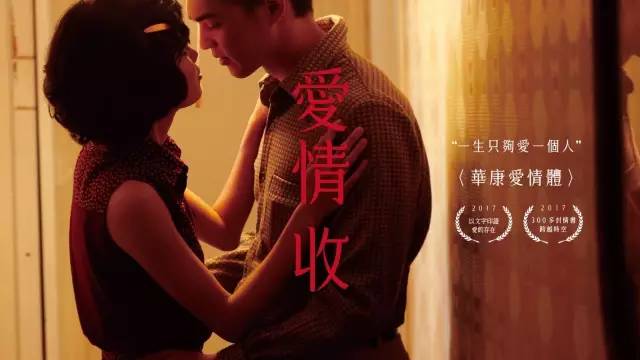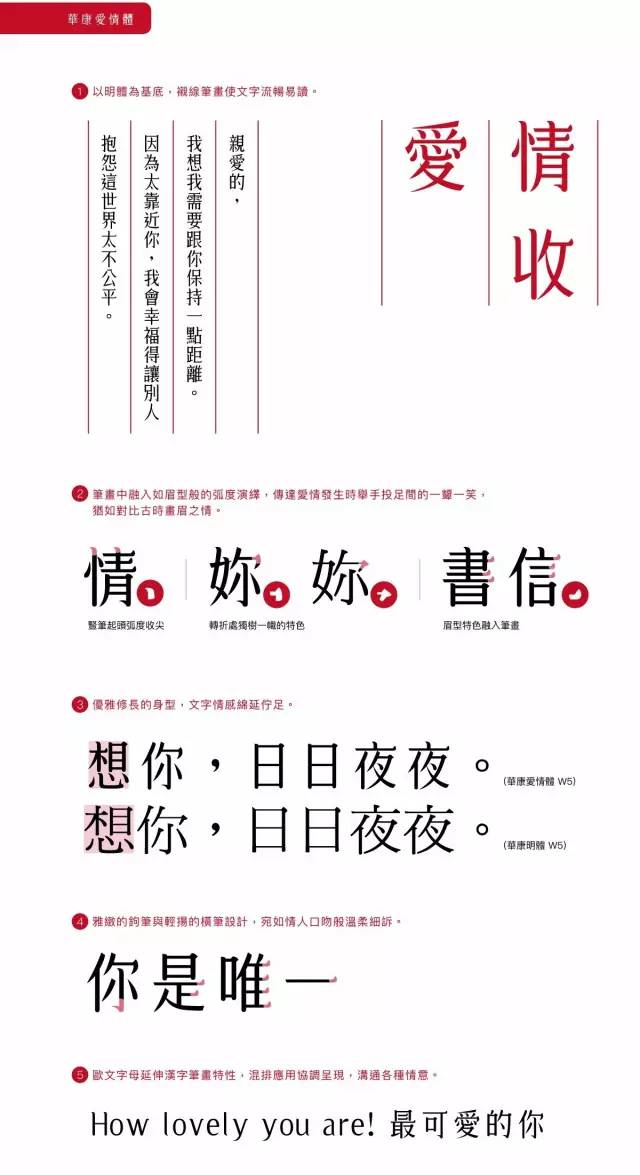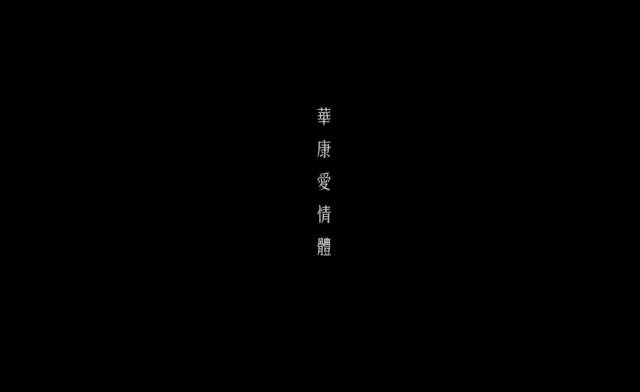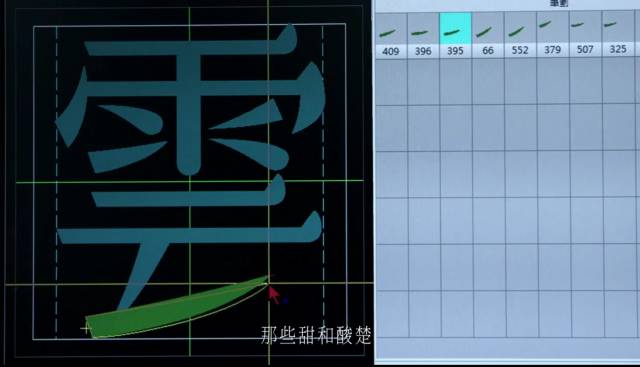
华康爱情体,这字体是跨越半世纪的爱情故事
我们有幸与一则半世纪前深刻的爱情相遇,故事的男主角国辉透过手写情书,以文字勾勒他和女主角云爱情的形状,以文字许诺他俩间爱情的重量,三百多封的〈邱月云小姐收〉,经纬交织成炽烈真挚的故事,字字印证了爱情的存在,也印证了他们的存在。然而这份爱情不只属于他们,我们更探寻那一笔一画之所以成为爱情载体的原因,将文字的情意汲取而出,凝聚出足以表述爱情的字型,华康爱情体。
关于《爱情收》
-起-
故事的主角钟国辉,在户政事务所负责誊写各式各样的户籍资料,每日亲笔书写人们的出生、死亡、结婚、迁徙,犹如爱的诞生、逝去、结合、分离。
十九岁那年,他认识了杂货店老板的十七岁女儿,邱月云。此后他振笔疾书的不再只有别人的人生,还有三百多封趁工作时偷偷写给邱月云的情书,每一个字迹都装载着爱。钢笔写下的每个字迹,拆开来看,和那些冰冷的生死文件并无不同;但在赤红的十行信纸中串联,却是浓密炽烈情感的倾泻。
「亲爱的云,我有说不尽的情意,……」薄薄一张信纸能承重多少?他未曾想过。他只知道每每拿起笔来,就想倾尽心中所有的爱,仿佛信一送出,吻就能到达对方颊上。
-承-
国辉修长翩然的字,悉心刻划与月云的爱情,时而激情、时而日常。
「附带寄给妳一个吻吧,吻在妳身体允许我吻的地方,反正随便妳的安排吧!」
「前几天妈买了许多小鸭子来饲养着,妈说是养着等妳回来端节为妳加菜之用,到时我也可托妳的福而大打牙祭呢!」
一九六五年,他们结婚。两人的身份证写上彼此姓名,户口名簿添了新生儿,随着手写的「迁入」两字展开新生活。这些笔画都扎扎实实地写进他们的旅程中,对两人而言,白头到老不仅是美好想像,更是个必然的人生里程。
-转-
三十年后的一个下午,钟国辉意外身亡。两人将至的未来,在远方戛然而止。此后,邱月云独自渡过无人知晓的七千六百多个日子,直到二○一五年离世。次女钟慧君整理邱月云遗物时,意外从衣柜深处取出一个陈旧斑驳的铁盒。
打开一看,竟是父亲写给母亲的三百多封情书;父亲字迹如新,信封也仿佛才刚被母亲急急地拆开而已。
看到这三百多封情书被如此妥善地保存,至此已不忍想像,过去二十一年,邱月云是如何熬过辗转难眠的孤独长夜,又是第几次深夜起身,念起当时的一切如常,于是再次开信,反覆读到信纸渐薄透光。
-合-
这些文字如钟国辉仍在左右一般,陪伴了邱月云长达二十一年,字字印证了爱情的存在,也印证了他们的存在。然而,这份爱情不只属于他们,更属于你我。
因为文字,我们存在、华康字型存在,我们探寻这三百多封书信中的情意,与古今之爱情作对比,探索那一笔一画之所以成为爱情载体的原因,最终凝聚出足以表述爱情的形状。将国辉每一封情书中手写的温度与情意,淬链、凝聚,让其修长翩然的字迹比之于优雅的字型结构;炽烈真挚的爱意,则以具象的雅致勾笔、与轻扬的横笔设计揣度,宛如情人口吻般温柔细诉。华康爱情体,属于你我爱情的字型。
爱情的模样
爱情萌芽之际,许多情感的流动来自眉目传情。华康近距离探寻《爱情收》主人翁书写爱情时的喜怒哀乐,从字里行间看见爱情充满生命力的流动,将文字的情意汲取而出,对照古时男女间的画眉情怀,发觉爱情的晶莹之处便是凝聚在这眉梢的一颦一笑。深刻探究后更确信,渴望质朴而炽烈的爱情,是始终存在的人性;无关时间的流动,古今相同。如此细细比对思忖,第一套属于爱情的字型便酝酿而生。
因此在台湾,我们赋予此字型爱情之名,正式称为《华康爱情体》。
DynaFont爱情体的字型特色
华康爱情体以明体为基底,衬线笔画使文字流畅易读;雅致的钩笔与轻扬的横笔设计,之于字体有如眉毛之于眼神,点缀喜怒,为字字注入饱满情绪,更能表现文意的抑扬顿挫。字型结构中更蕴藏了些许强调姿态与气质的复古情怀,特别适合用于传情达意。倘若文字有声,你便会听见气质出众的优雅声线。
生活中爱情的伫足
当爱情来到生活里,处处可见爱情将至或走过的痕迹;无论是暧昧时精心化的妆、为重要时刻精挑的一身衣裳,或独自思念时所读的文章。华康爱情体已准备在爱情发生之处为品牌发声,特别适用于美妆、时尚、艺文杂志、风格品牌等领域,应用范围包括杂志标题、包装设计、电影海报、广告用字及复古典雅的商品。
他们的爱情,未完待续……
华康字型特别将国辉与月云《爱情收》的故事,以影像的方式,带到2017年的现在,与你相遇。摄影、灯光、美术、造型、35mm胶片等,我们启用电影班底与规格,从2016年冬天积极制作这部短片。阅读男主人钟国辉三百多封手写情书,有幸共享他与邱月云的爱情,信里有青春的气味,有炽烈的思念,有对相守的憧憬,以及黏腻的蜜语中夹杂着家常的对话,ㄧ如我们所有人谈过的恋爱。现在,你可藉由影片品尝半世纪前字里行间的浓烈情意,让感官随影像,回到专注而缓慢的年代,一同感受文字成就的隽永爱情。
本片根据真实故事改编